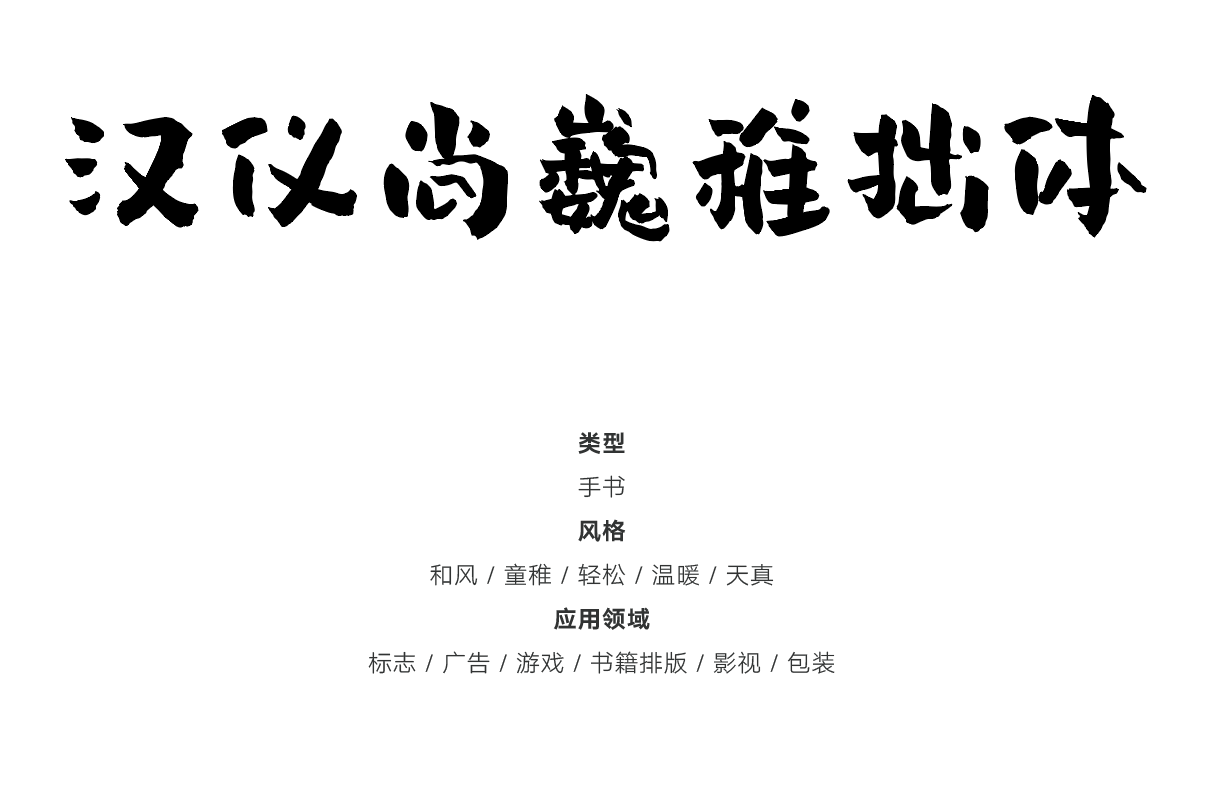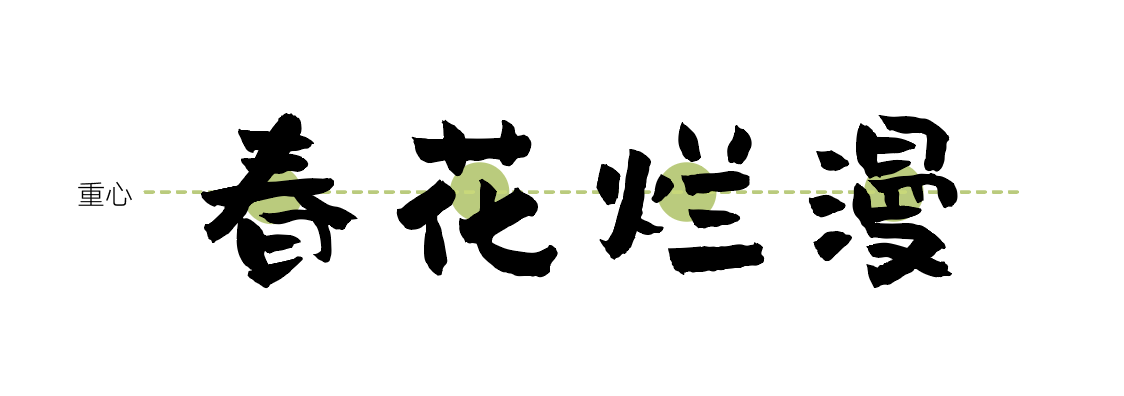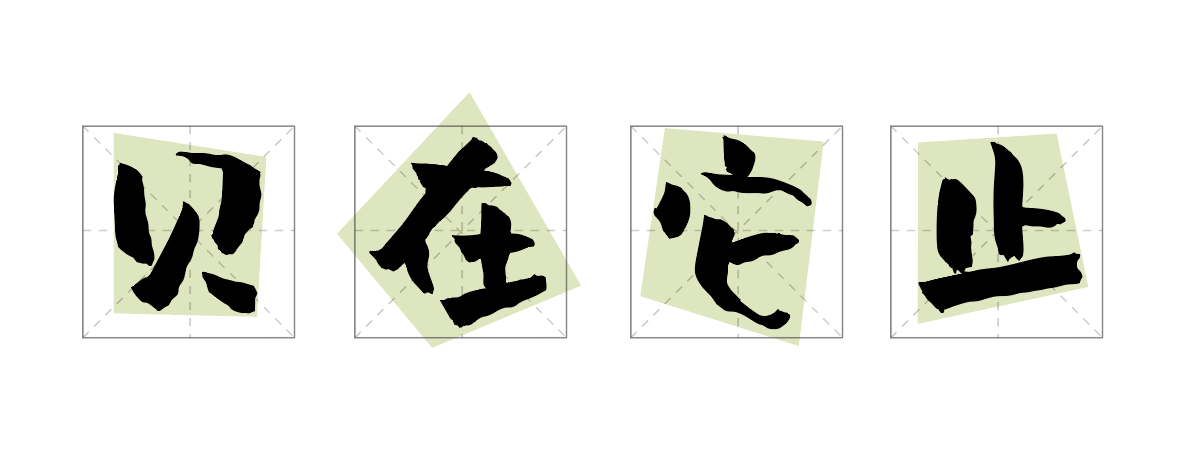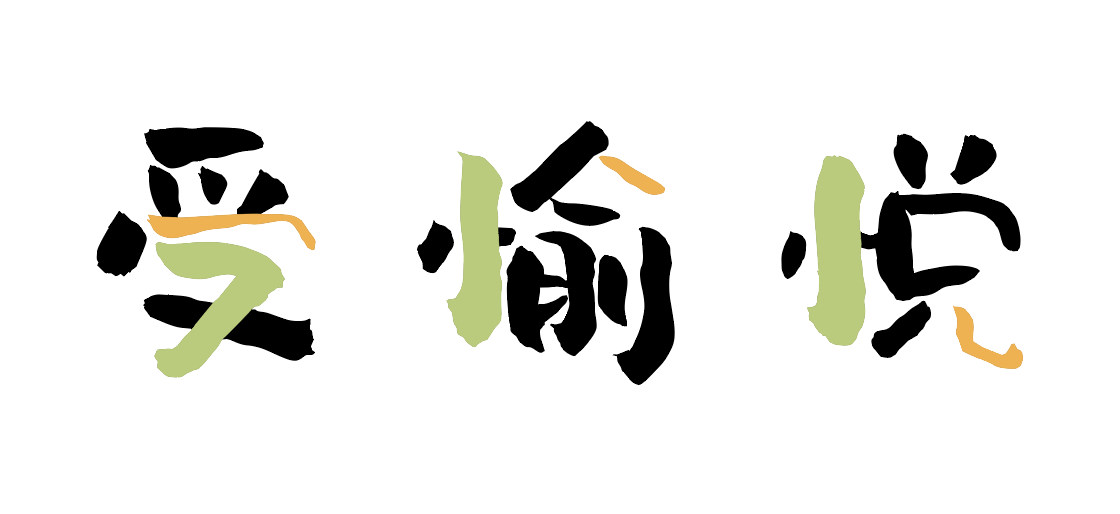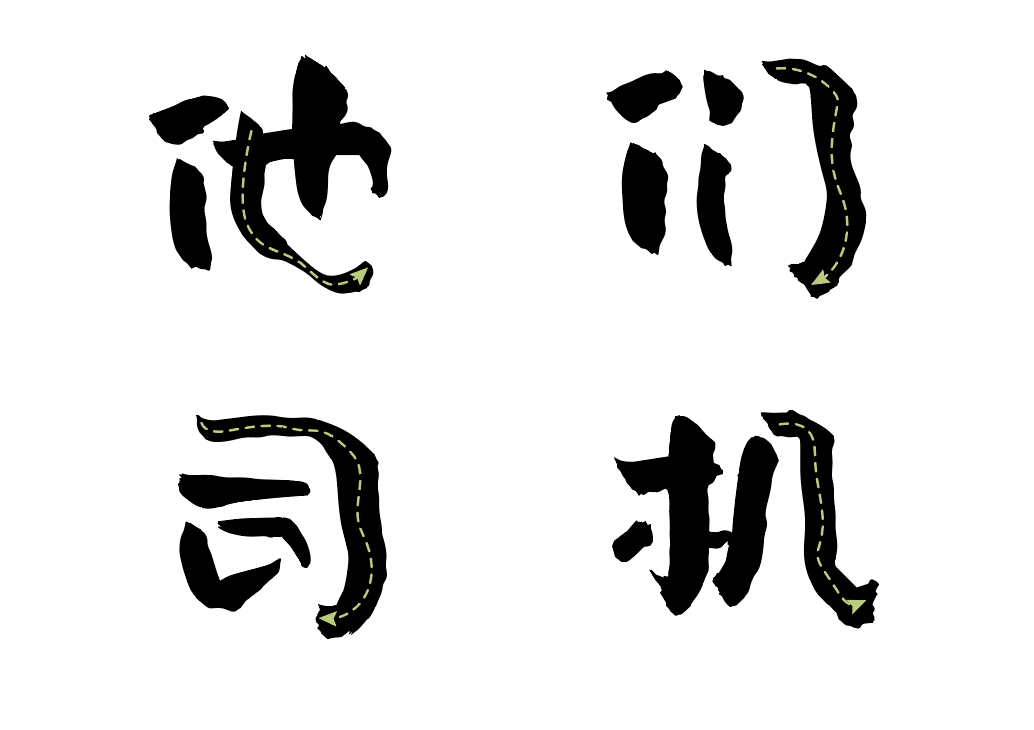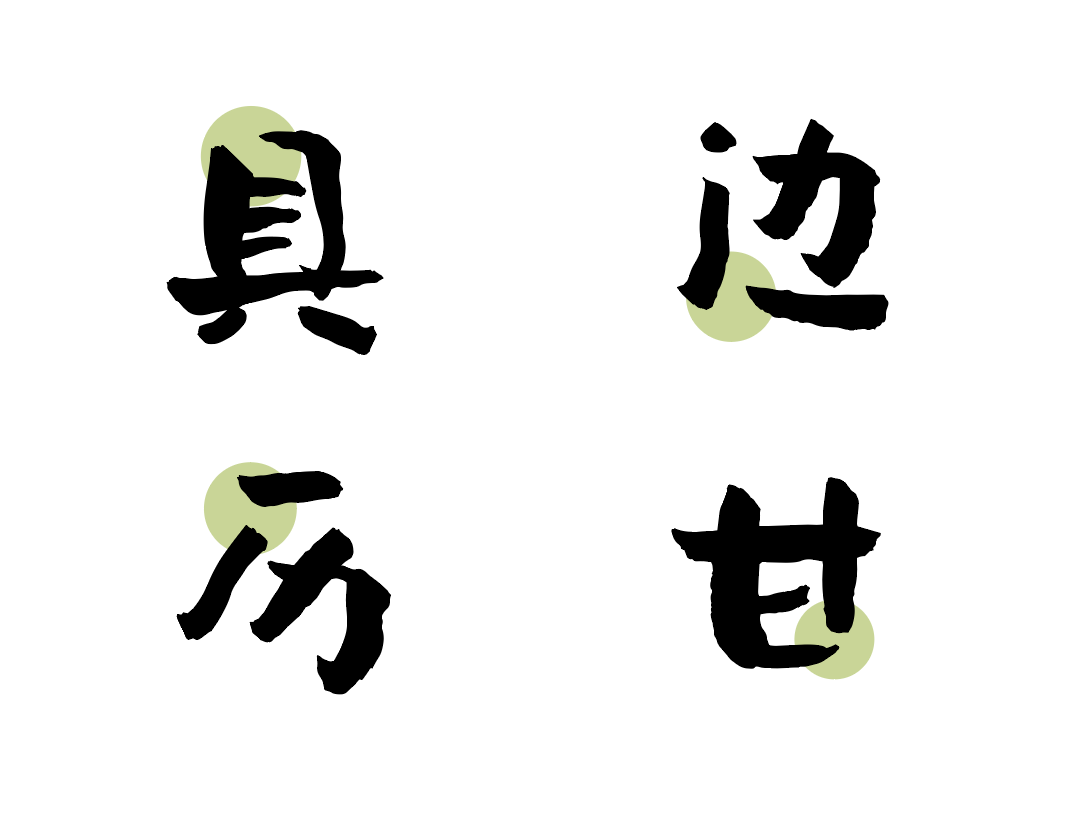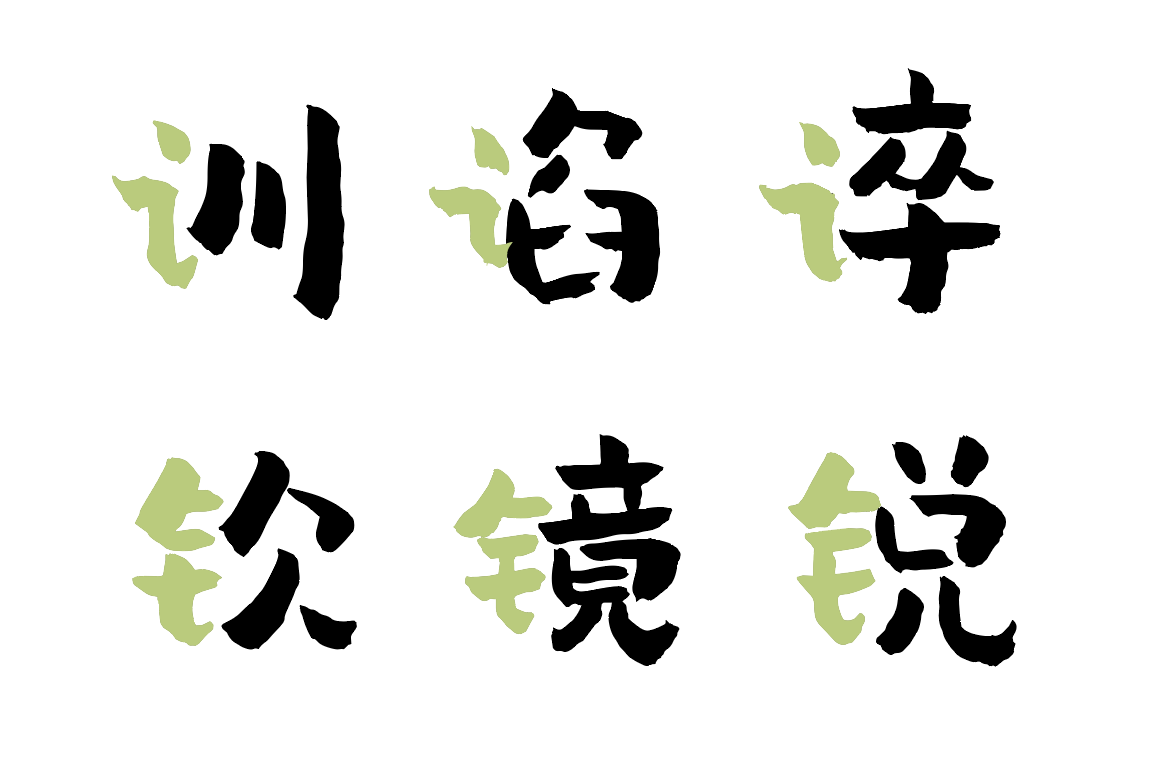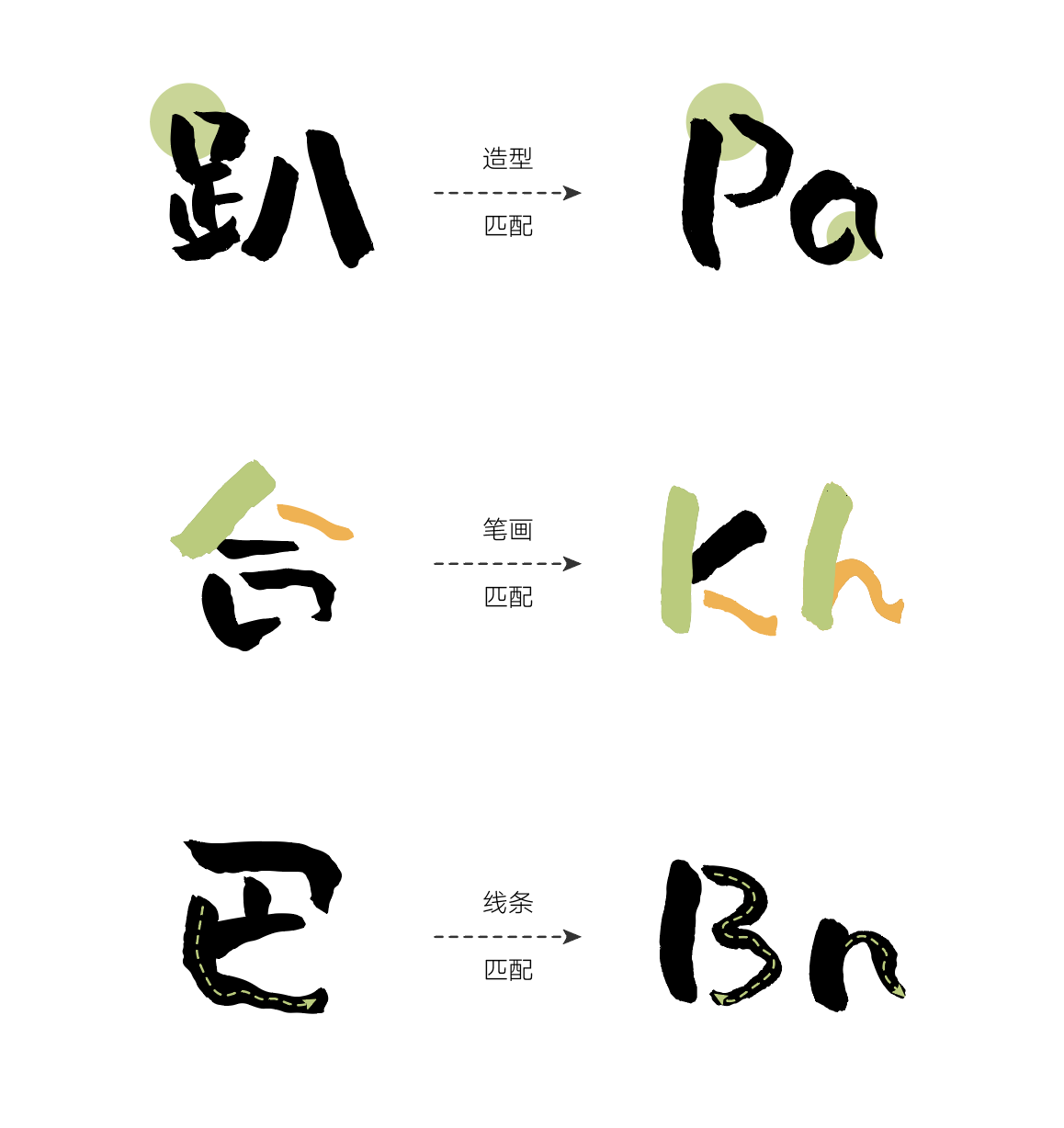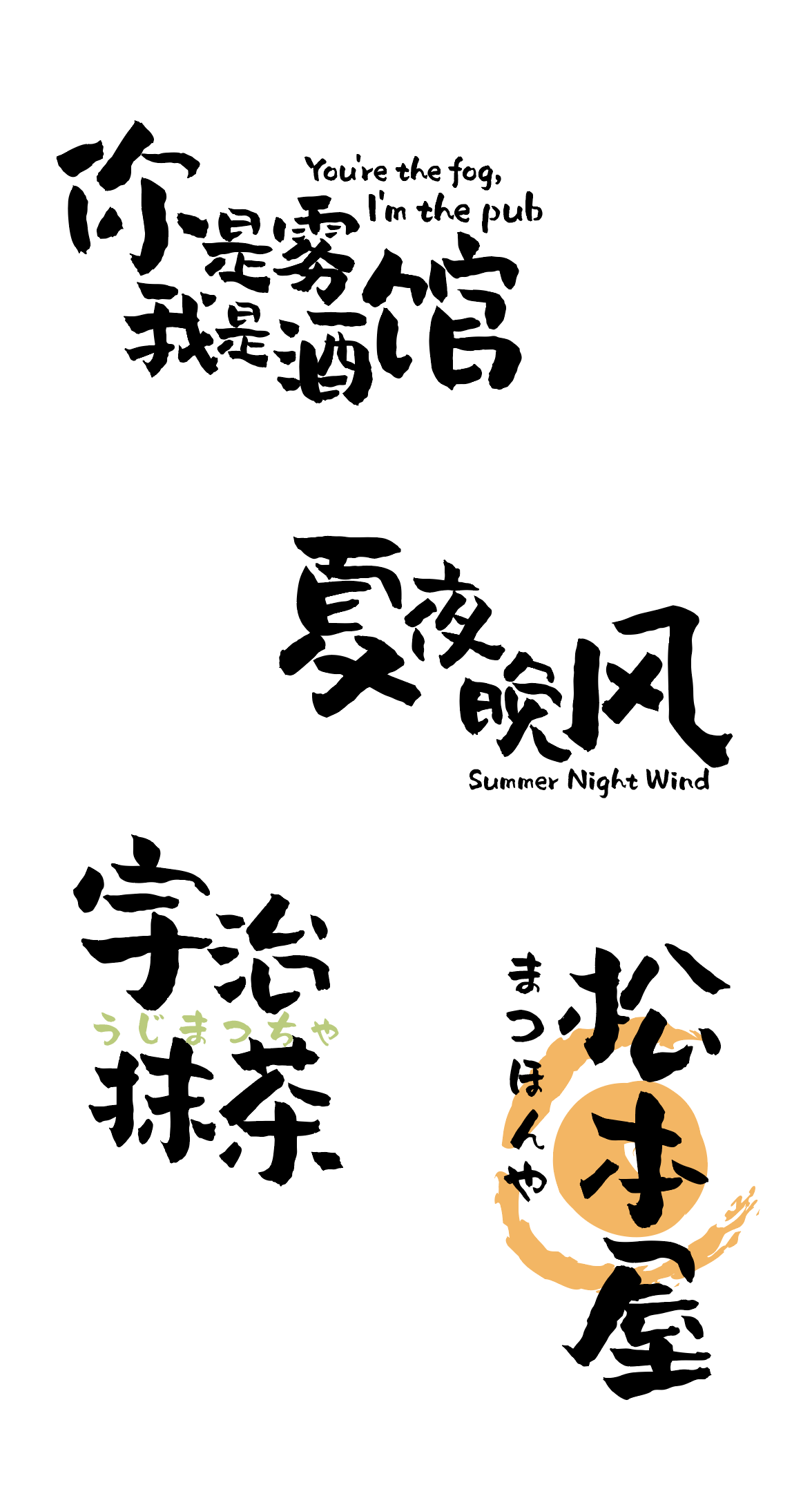
汉仪尚巍稚拙体 详情页
字体名称: 汉仪尚巍稚拙体
汉仪尚巍稚拙体
汉仪尚巍稚拙体 | 天真稚拙
汉仪尚巍稚拙体为90后新锐字体设计师尚巍所做的一款有着日和风格的手书字体。作者在书写时处于非常放松的状态,使得字体给人一种轻松缓和的视觉效果,非常具有亲和力。
汉仪尚巍稚拙体 | 字形多变
汉仪尚巍稚拙体的字形布局考究、张弛有度。笔画排布看似随意却又能够在视觉上保持统一,给人带来温暖的松弛感和亲切感。
汉仪尚巍稚拙体的结构多变,部分字形打破常规。虽然看似放纵随意,但其实每个字都被限制在字框中。
汉仪尚巍稚拙体 | 笔画童稚
汉仪尚巍稚拙体笔画的粗细变化十分明显,作者用笔时而坚实有力,时而顽皮随性。
汉仪尚巍稚拙体的书写手法质朴拙嫩、直率自然,笔画提按过渡明显,线条变化自由生动,看似如儿童书写般弯曲随意却又带一股力度和韧劲。
汉仪尚巍稚拙体在笔画衔接处的留白让人联想到儿童在写字时的笨拙可爱,生命力表现十足。
汉仪尚巍稚拙体保留手写的独创性,减少机械复制,使相同的偏旁出现不同的手写效果。
中西文匹配
汉仪尚巍稚拙体的西文充分吸收了中文笔画造型和线条的特点,形成了带有朴拙韵味、风格童稚天真的字母。中西文搭配使用时和谐统一。
排版效果